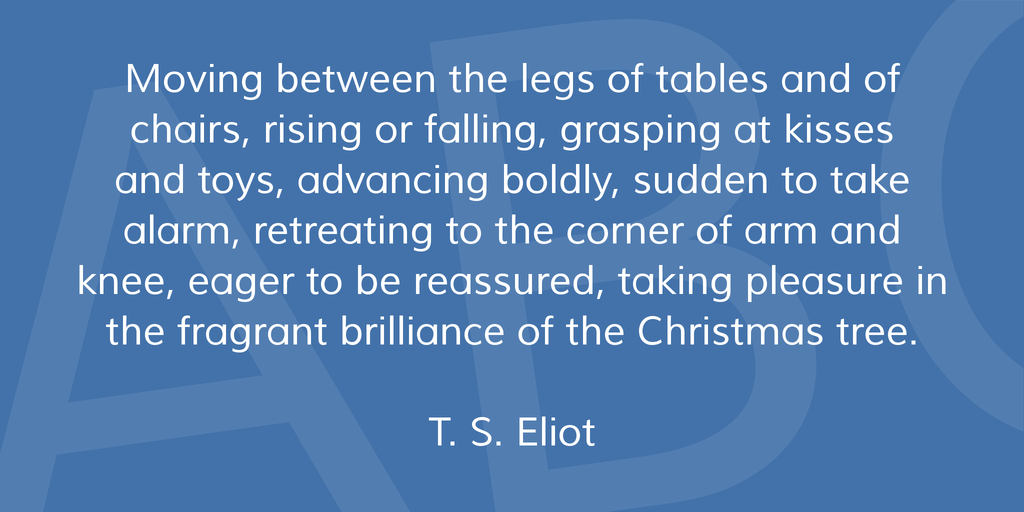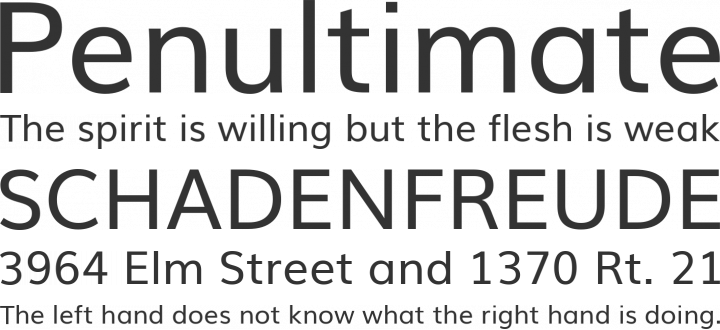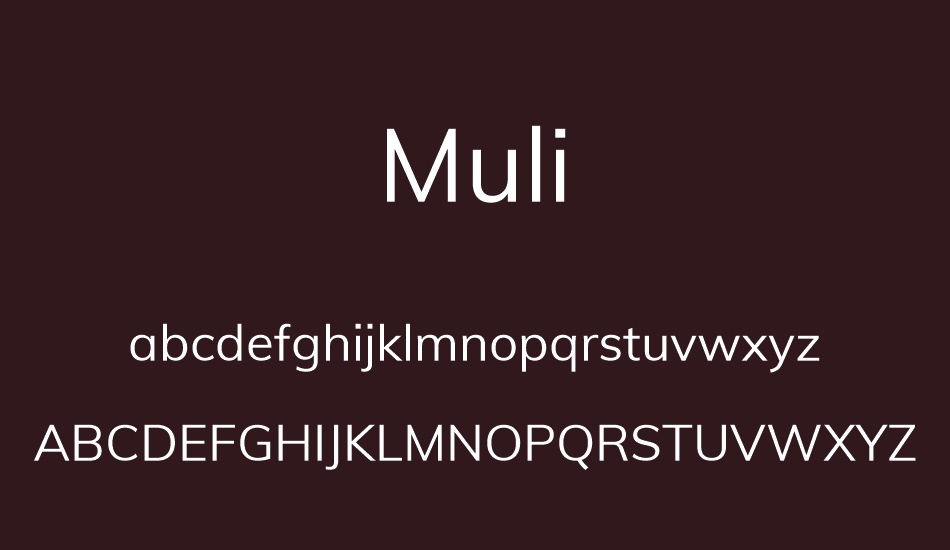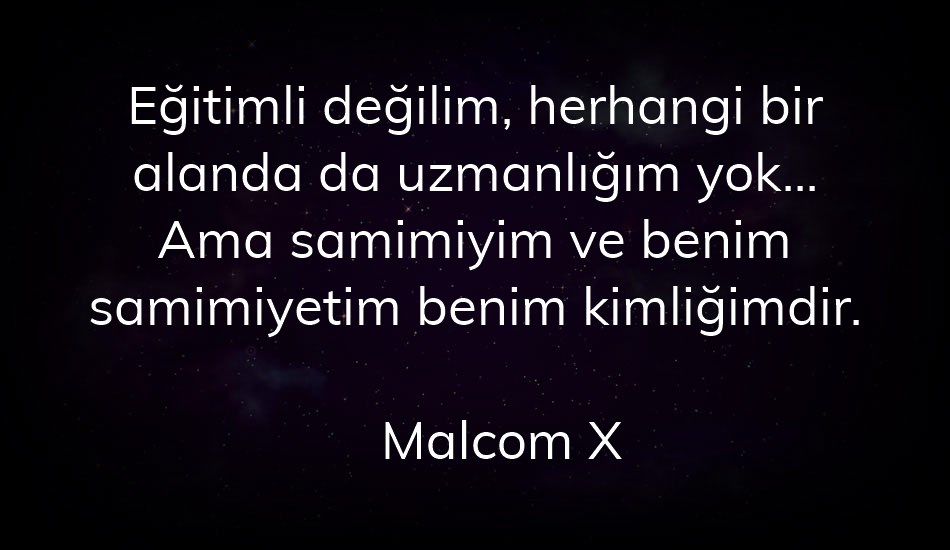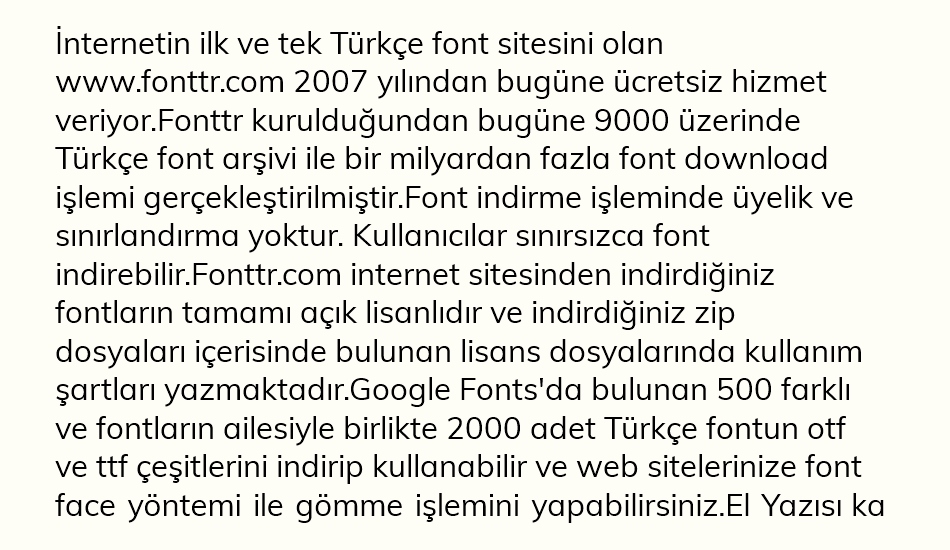
Muli Font minimalist bir Sans Serif. Muli çoğunlukla bir ekran yazı tipi olarak kullanılmak üzere tasarlanmıştır, ancak bir metin yazı tipi olarak da kullanılabilir. Muli, masaüstü bilgisayarlar, dizüstü bilgisayarlar ve mobil cihazlardaki web tarayıcıları tarafından internette özgürce kullanılmak üzere tasarlanmıştır.
Muli font